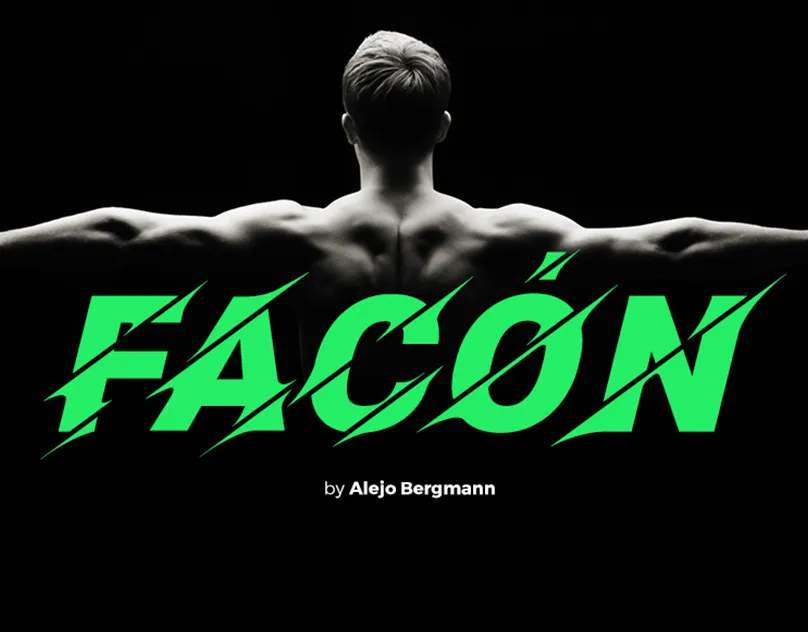
Introduzimos a Facón Typeface, uma fonte tipo impressão com cortes diagonais criada por Alejo Bergmann. Esta fonte é perfeitamente adequada para fins de exibição variados como logotipos, selos e rótulos, headlines e banners, impressões de revistas e muito mais. Com seus caracteres em caixa alta completos e números e símbolos presentes, a Facón é uma escolha ótima para quem busca personalidade. Suas diagonais proporcionam um toque moderno à qualquer design que use, tornando-a perfeita para ambientes de exposição. Seja em um logotipo ressaltando a marca ou em um selo distintivo, a Facón é uma ótima escolha para aquilo que deseja destacar na sua próxima impressão.
Designer: Alejo Bergmann